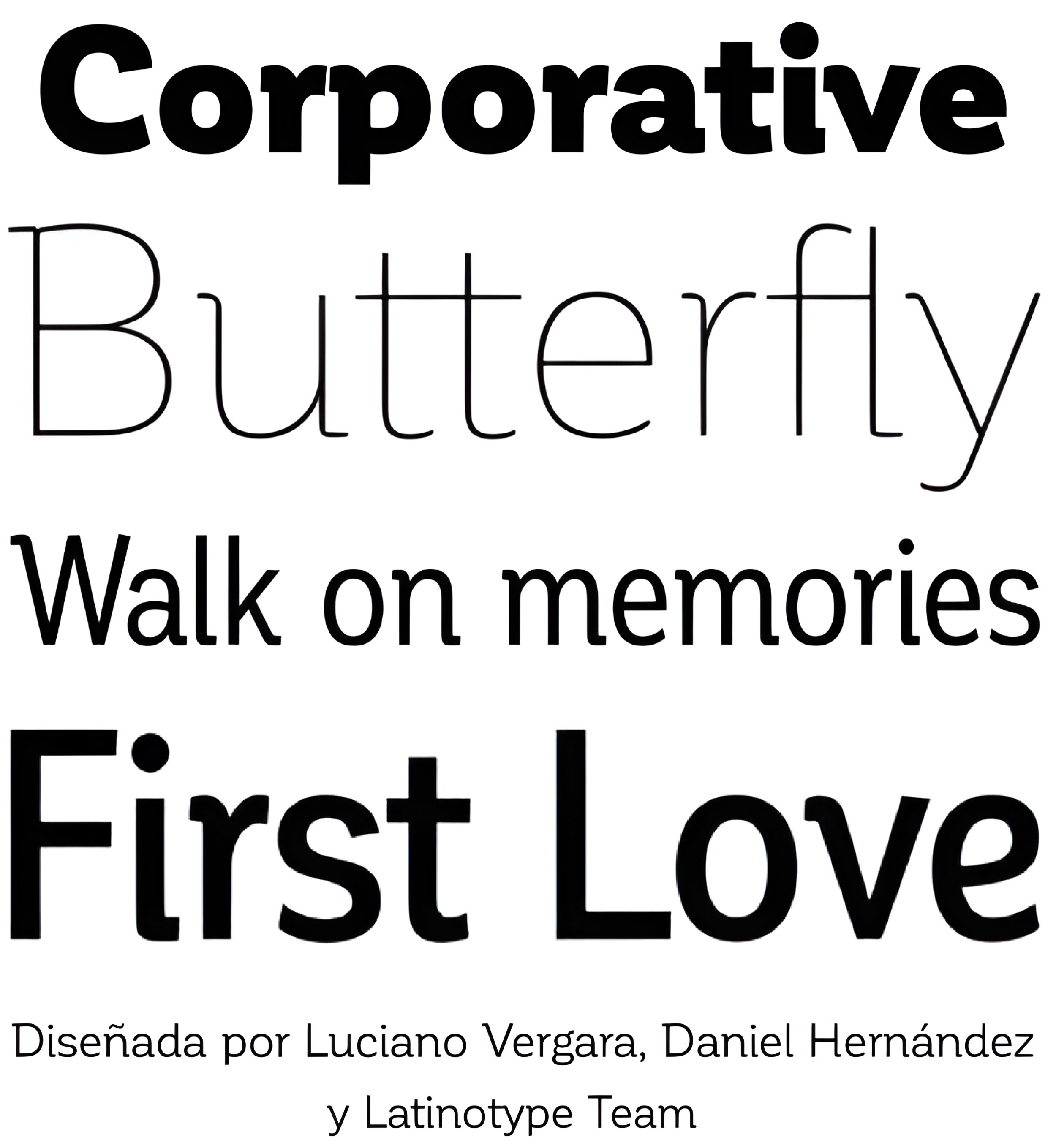
| Año | 2015 |
| Créditos | Luciano Vergara, Daniel Hernández |
| Descripción | El primer tipo de letra desarrollado por Latinotype Team. Corporative es una fuente semi serif que tiene una marcada personalidad y rasgos distintivos, lo que la hace adecuada para ser utilizada en tamaños de texto grandes. Al ser una fuente condensada, también puede utilizarse en tamaños más pequeños. Corporative y Corporativo Sans vienen con el juego estándar de 350 caracteres de Latinotype, lo que permite utilizar la fuente en 128 idiomas diferentes. Corporative ofrece a los usuarios una amplia gama de caracteres, pesos y anchuras para cada proyecto. Combinando distintas variantes, los diseñadores pueden conseguir los mejores resultados. La familia consta de 64 fuentes: una familia básica que incluye 8 pesos más cursiva, una familia alternativa de 8 pesos con cursiva a juego y 2 familias condensadas, una normal y otra alternativa, ambas con cursiva. Latinotype ha incorporado nuevas caras a su equipo. El equipo de Latinotype se compone ahora de: Javier Quintana, César Araya, Bruno Jara, Luciano Vergara y DanielHernández. Corporative fue creada por Latinotype Team y desarrollada por Javier Quintana y César Araya, bajo la supervisión de Luciano Vergara, Miguel Hernández y Daniel Hernández. |
| Familia(s) | Corporative |
| Estilos | 64 |
| Estudio | Latinotype |